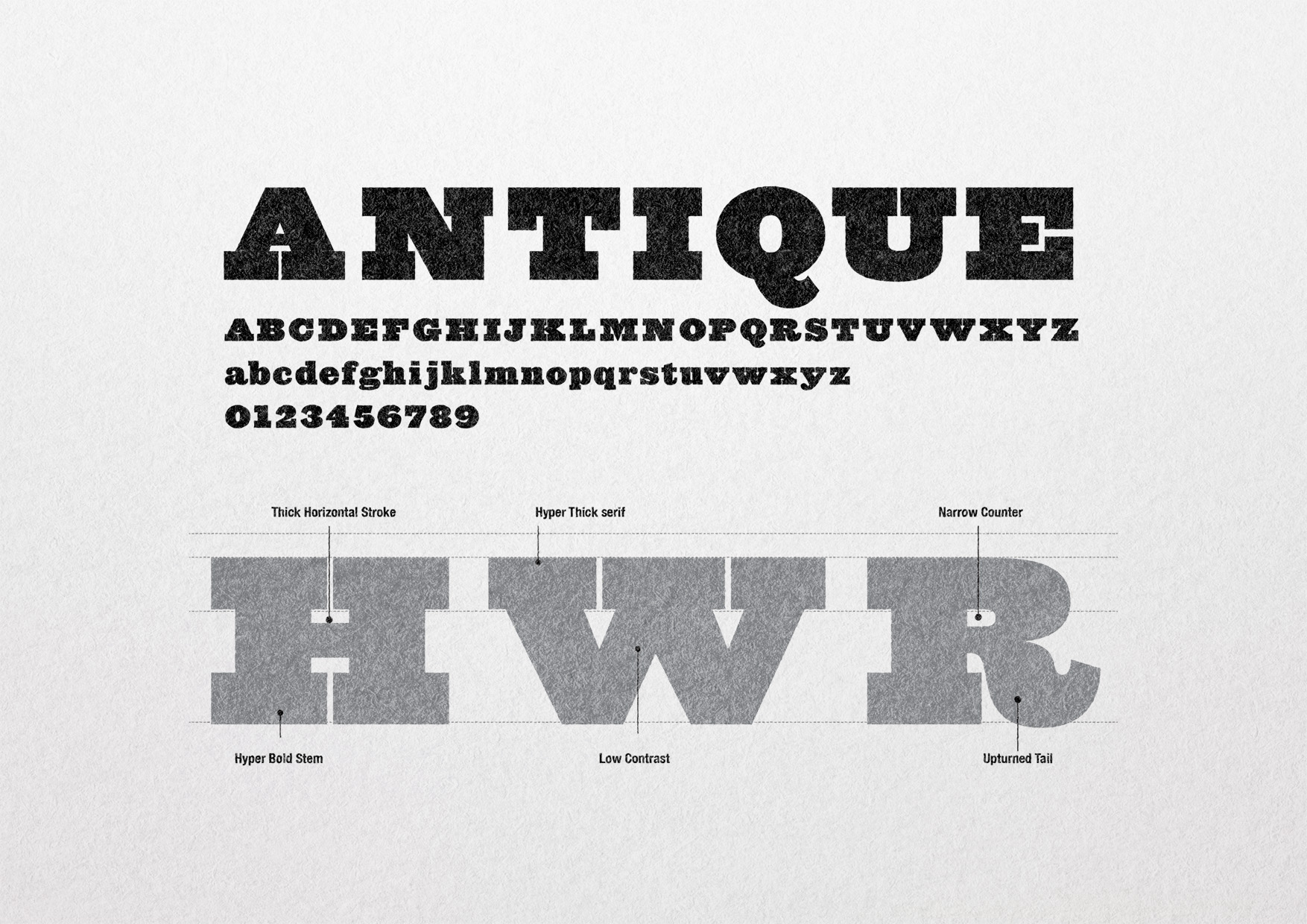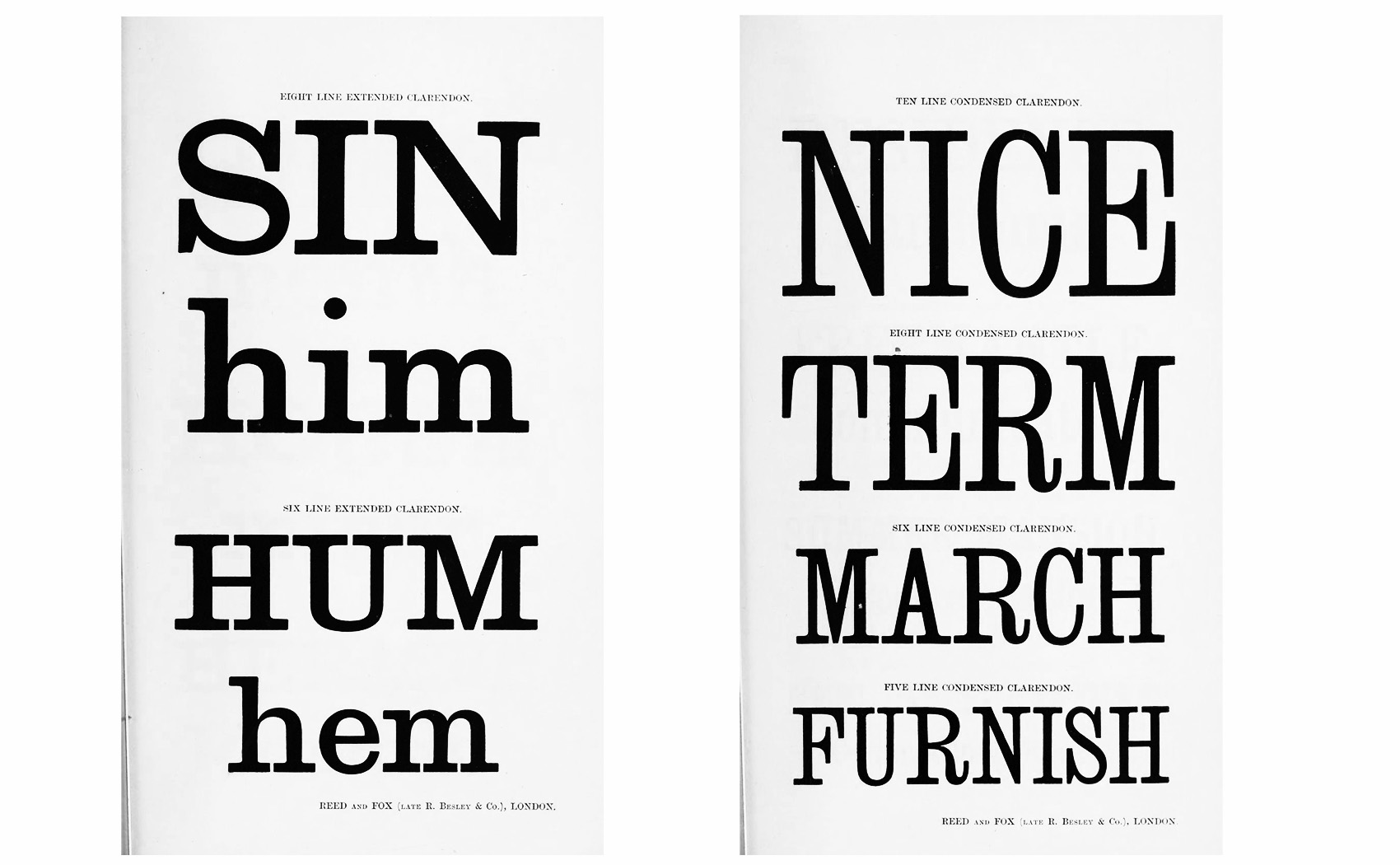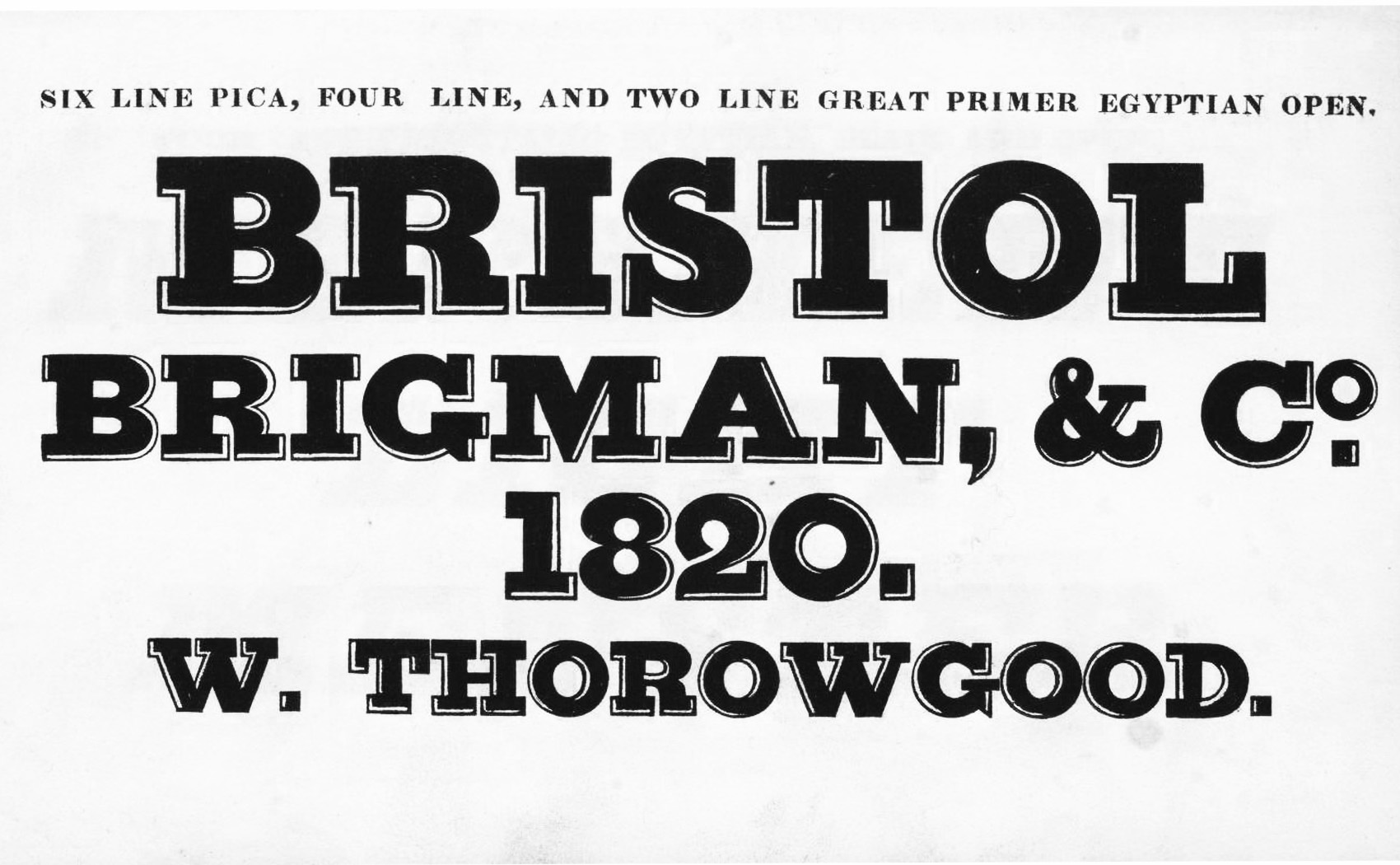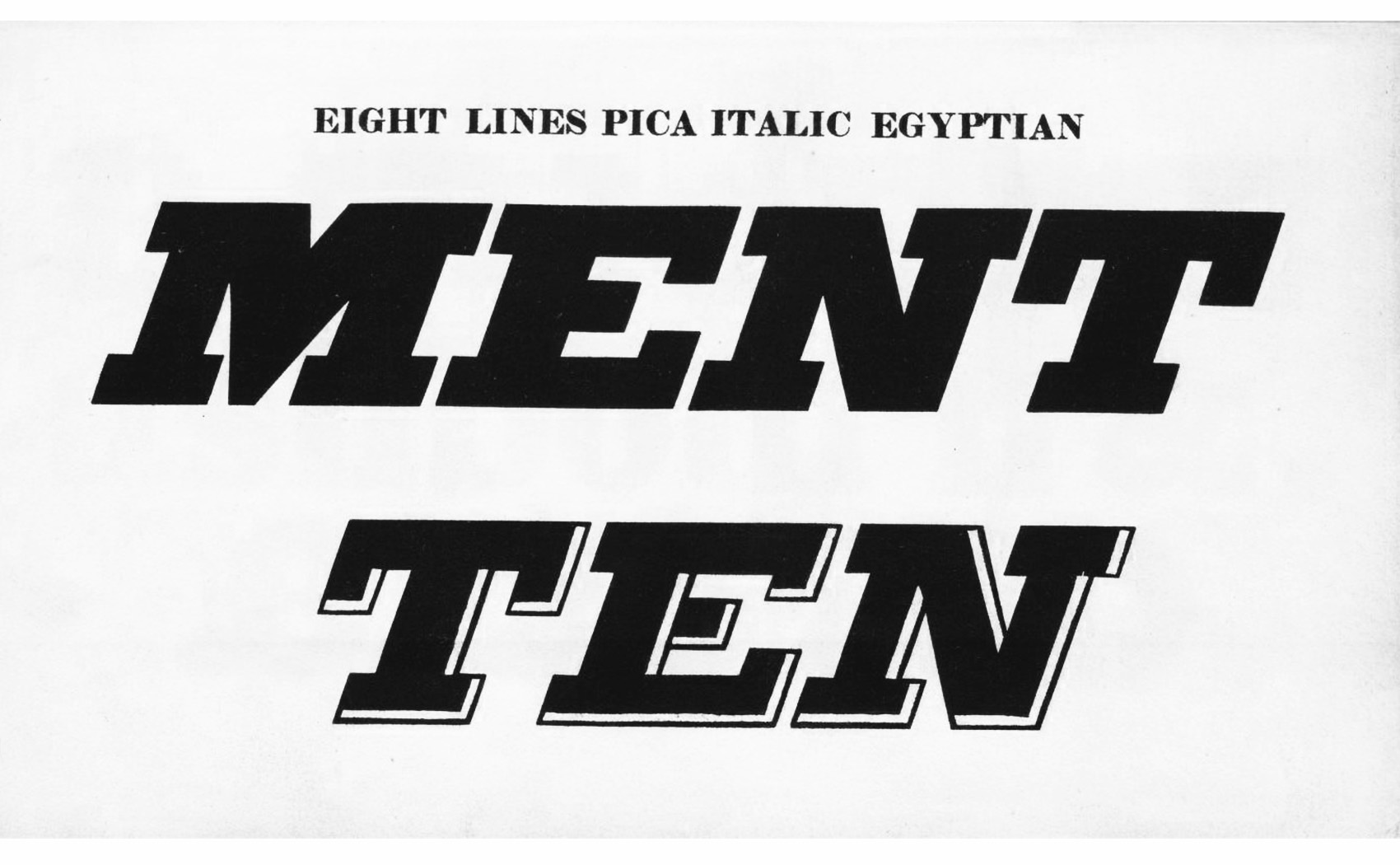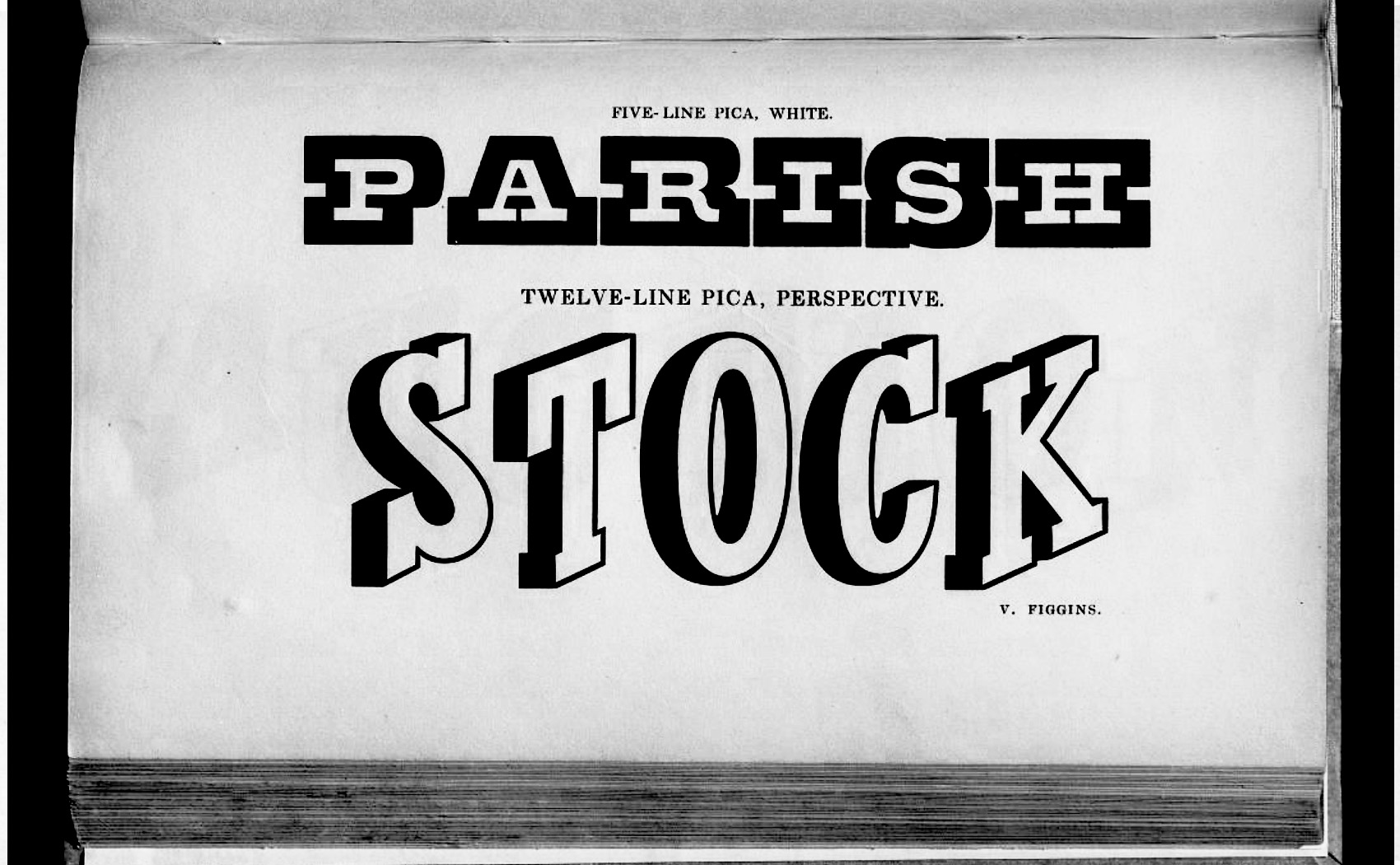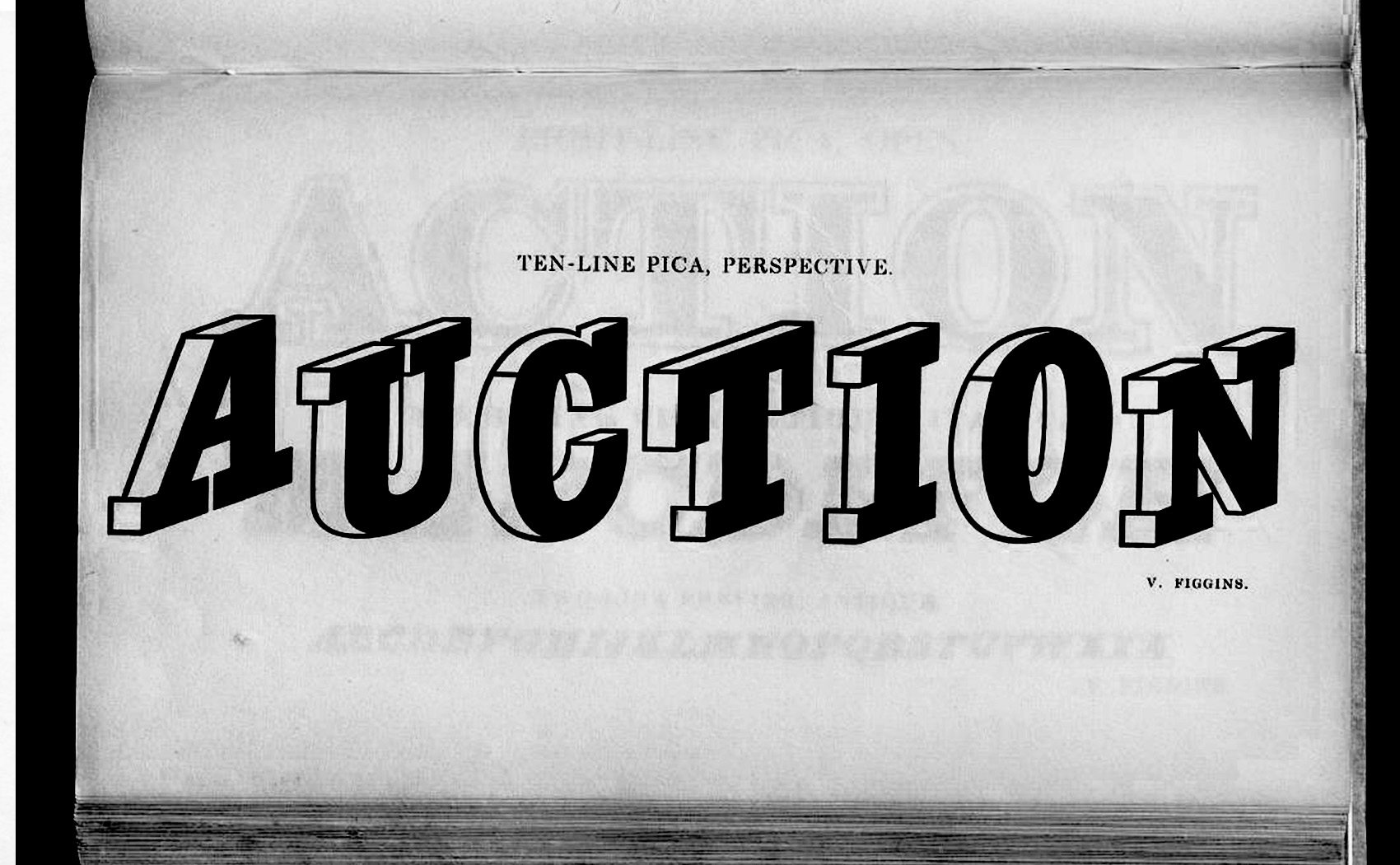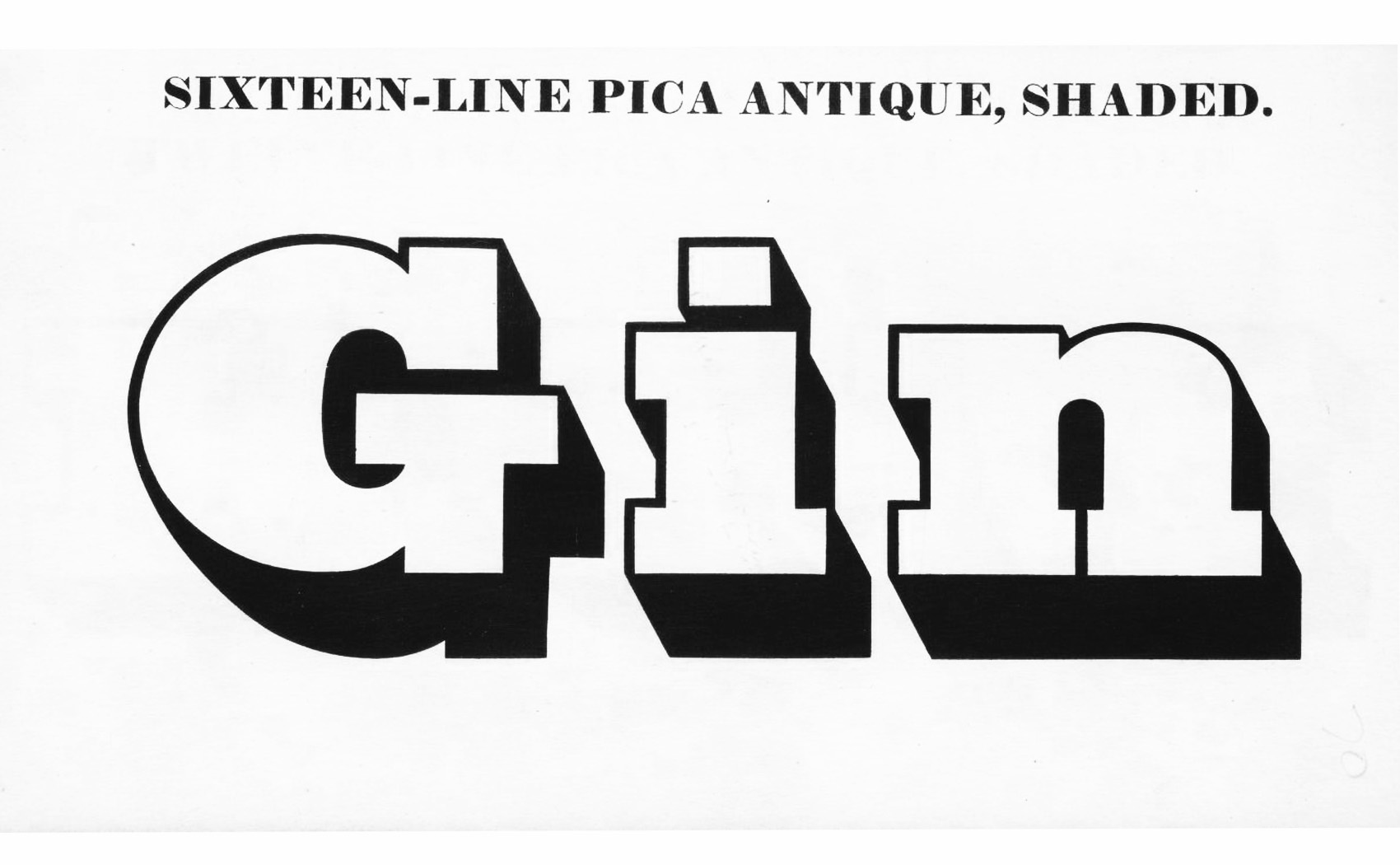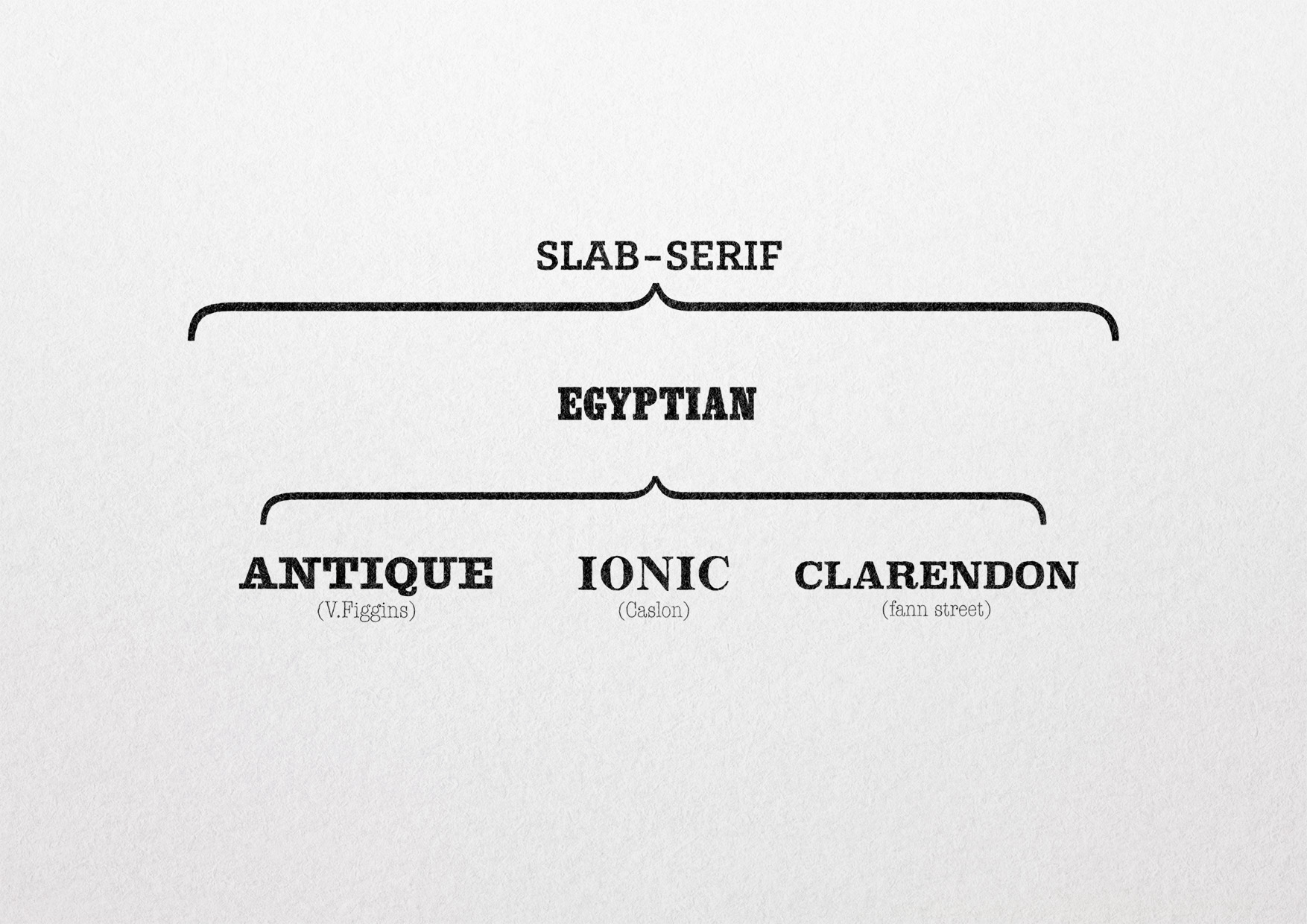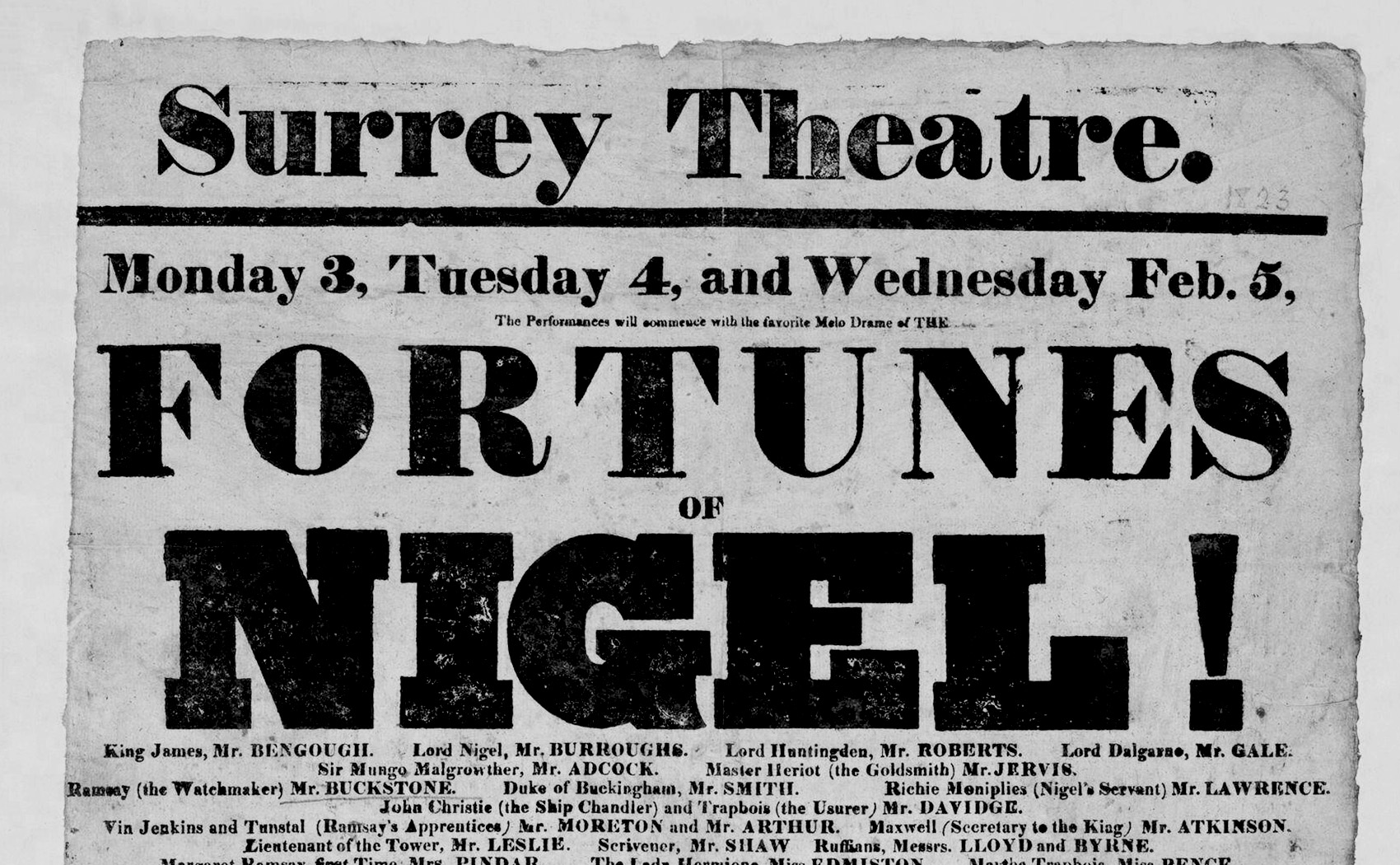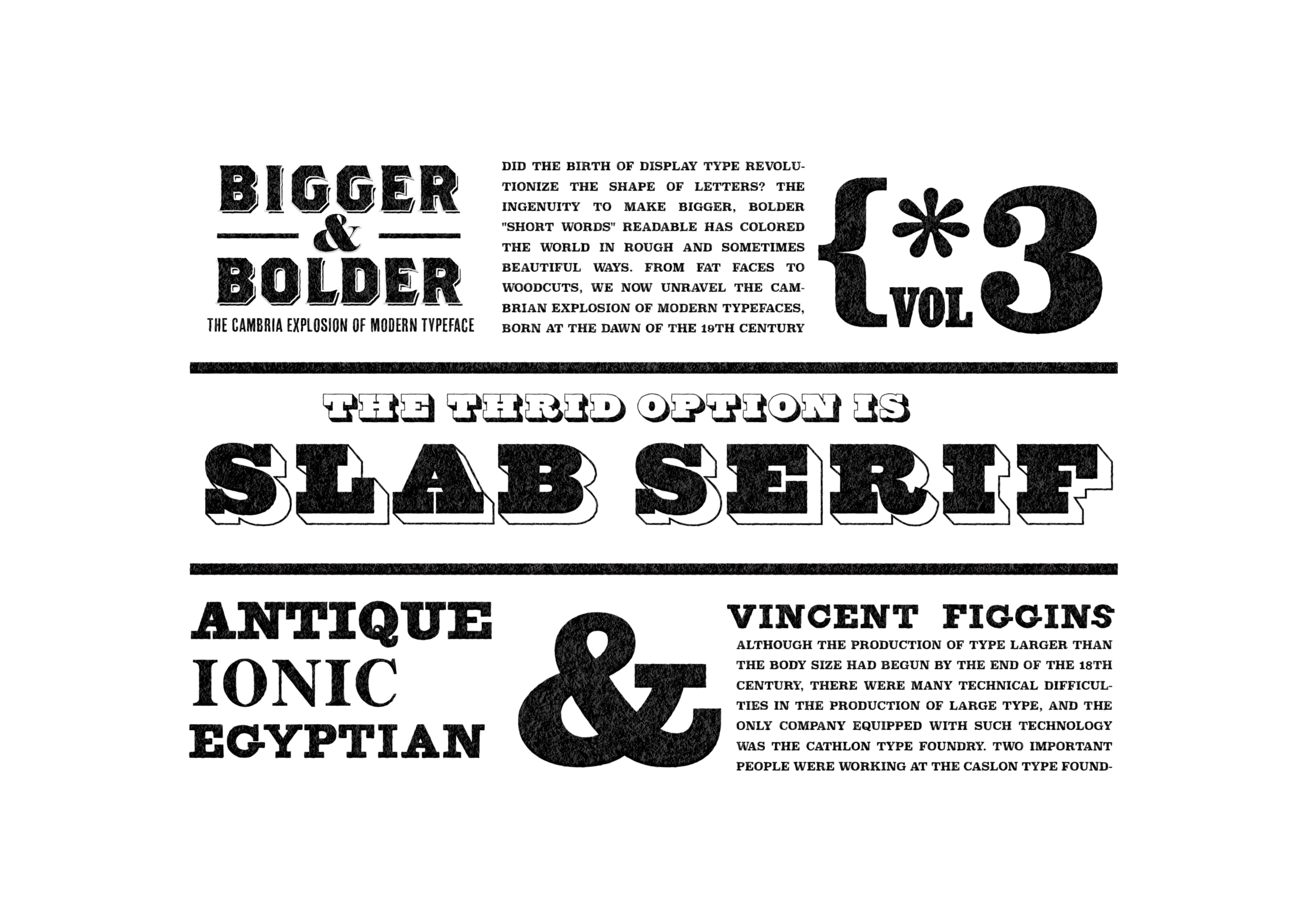
BIGGER & BOLDER
The Cambria Explosion of Modern Typeface
Did the birth of the display typeface revolutionize how letters look? The devices used to make bigger, bolder, “short words” readable have colored the world in rough and sometimes beautiful ways. From fat faces to woodcuts, we now unravel the Cambrian explosion of modern typefaces, born at the dawn of the 19th century and buried in the shadows of history.
THE THIRD OPTION IS SLABSERIF
第三の選択肢スラブセリフ
ファットフェイスが開拓したディスプレイタイプのデザインというフィールドを次に底上げしたのはスラブセリフでした。「大きい活字」「太い活字」を継承してさらに目立つ黒味の追求をセリフへと手をつけてゆくことで全く新たなジャンルを切り開いてゆきました。ローマン体がモダンになるためにダイエットしてきたあのセリフを、ファットフェイスすら拒んだセリフをこともあろうに極限まで太らせたのです。しかし、その新たな形、あらたなデザインはさまざまな可能性を切り開いてゆきました。縦横のコントラストをはじめこれまでの保守的な価値観を崩壊させ、視認性という一点で誰よりも意味のある存在に変わっていったのです。19世紀のロンドンから始まりアメリカへわたり、21世紀にいたるまで広告や雑誌、新聞、タイプライター、プログラムのコーディング用にと日常的に身近に存在し第一線で活躍するタイプフェイスのスタイルへと上り詰めた、そんなスラブセリフの旅路についてのお話です。
Slab serifs were the next step up in the field of display type design pioneered by Fat Face. By continuing with “large type” and “thick type,” Fat Face opened up a whole new genre by pursuing a more prominent black tone in the serifs. The Roman type had gone on a diet to become modern, and the serifs that even Fat Face refused to use were fattened up to the extreme. However, the new shape and design opened up a variety of possibilities.The typefaces collapsed the conservative values of the past, including vertical and horizontal contrasts, and became more meaningful than anyone else in terms of a single point: visibility.This is the story of the journey of slab serifs, which began in London in the 19th century, traveled to the United States, and then rose to become the leading typeface style in everyday life, present in advertisements, magazines, newspapers, typewriters, and for coding programs through the 21st century.
TYPE DESIGN OF SLABSERIF
スラブセリフのタイプフェイスデザイン
SLABSERIF
Slab serif is a style classification of typeface design characterized by serifs that look like thick boards, as the word SLAB means thick board. Like the fat face, it is based on the modern serif design, but it is a design that began to move in a more geometric direction by changing the balance of vertical and horizontal lines in addition to the approach of thickening the lines. By thickening the thin horizontal lines, which are characteristic of modern serifs, instead of only vertical lines, the contrast ratio between vertical and horizontal line widths is reduced to create a strong black tone. In addition, by making the counter wider, the contrast between the ground and the figure is increased, thereby enhancing legibility and readability.
Clarendon/Ionic
Originally a typeface name, Clarendon as a classificatory term refers to typefaces that have the characteristic thick vertical and horizontal line widths of slab serifs, plus thick bracket serifs that bridge the gap between Roman and slab serifs. Both Clarendon and Ionic fall within the range of slab serifs when compared to roman and sans serifs, but are often used to further distinguish slab serifs because of their bracket serif characteristics.
The Birth of Slab Serifs
Slab serifs first appeared in the 1815 Figgins catalog sample book “ANTIQUE,” which is believed to be the first design with slab serif characteristics. Although it is very likely that the typeface itself was already in use in the area of signage, such as placards and sign painting, it is believed that “ANTIQUE” was the first design in typeface history to meet the current classification requirements for slab serifs. The general theory is that the design that meets today’s slab serif classification requirements was completed in 1815.
Specimen of printing types (Vincent Figgins,1821)
Typography
Slab serifs, like fatfaces, started out as a display usage for the purpose of conveying “short words” in “large type” on poster and playbills. If we check with playbills and other materials of the time, we can see that it was used for visual contrasts other than to contrast information with the typeface type by being used mixed with the preceding fatface. In contrast to the prominent hairlines and curves of fat face, the strong blackness and linear impression of slab serifs, which are similar to monolines, give the paper a more pronounced black color and leave a solid, geometric impression that follows the modern type used today.
Surrey Theatre(1823)V&A
Slab serif variation
As with fat faces, development by thickness and decorative variations are added in abundance: italic, open, as well as shaded (shadowed and three-dimensional).
Specimen of printing types(Caslon,son & Livermore,1830)
New specimen of printing types (W.Thorowgood & co,1825)
specimen of printing types (V&J Figgins,1836)
The Birth of Clarendon . From Display to Text
A little later, several variations of Figgins’ “Antique” design appeared, including a bracket serif uppercase “Antique” design around 1833, followed in 1842 by a similar lowercase “IONIC” design by Caslon Foundry. The “Antique” design with bracket serifs for readability was introduced in 1842. The design of the typeface, with its thick lines and bracket serifs that lead to easier readability, was also developed for use in the text.The Clarendon appeared in 1845 on Thorogood’s Fann Street.With its mild boldness and bracket serifs, Clarendon was a game changer and took the market by storm. Clarendon was the first typeface design in the world to be registered, and although it was copied by other foundries soon after the three-year registration period ended, it became so popular that it became a common noun for the style. The punch cutter Robert Besley (1794-1876), who designed it, would later become the mayor of London.
Selections from the specimen book of the Fann Street Foundry(Fann Street Foundry,1874)
As Bold in the body text
Before the appearance of Clarendon, the emphasis of this font was mainly in italics, and there was no concept of emphasis in bold. With the advent of Clarendon, the font was mixed with the Roman font, which was welcomed for its use as the bold of today’s fonts. This led to the development of a family of fonts that later developed into sans-serifs and other fonts with the same design and thickness.
• Egizano
Monotype’s Revived Vincent Figgins 1815 Egyptian
• Caslon iconic no2
Revival of Ionic in Caslon, complete from text to display.
• FIGGINS ANTIQUE
Revival of ANTIQUE by Vincent Figgins in 1815
• Monotype Clarendon
1845 Digital Revival of Clarendon designed by R. Besley